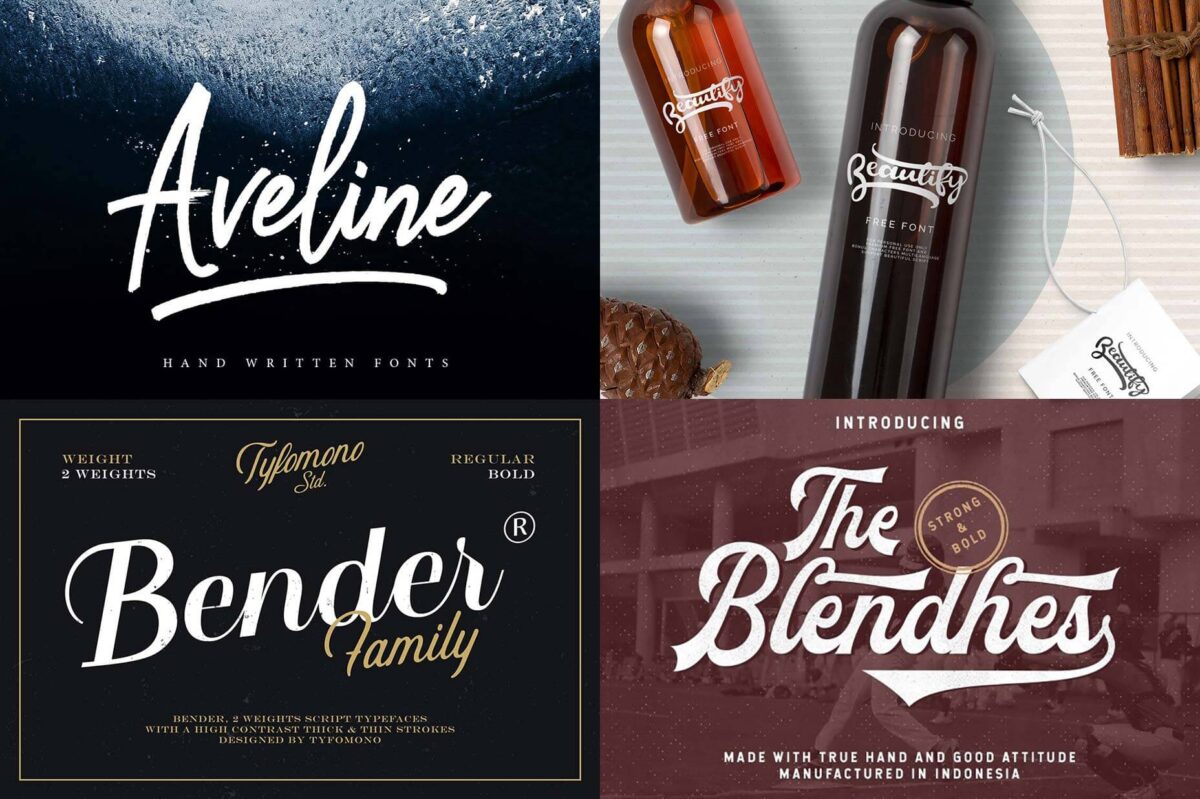
30 typographies commerciales à télécharger gratuitement
Nous avons toujours besoin de nouvelles typos. Ça tombe bien, webdesignerdepot et Mighty Deals proposent un pack de 30 typos à télécharger gratuitement.
Le pack de typo est très large et propose des choix très différents. Vous trouverez des typos très commerciales, des typos d’écriture à la main, d’autres au contraire font plus professionnelles. On sort clairement des typos habituelles du genre Helvertica et leur rigidité corporate. Certaines ne sont pas spécialement du meilleur goût, mais elles peuvent toujours se montrer utile pour certains projets et notamment pour du print. Pour télécharger les typos Alessandria, Andora, Anthasic, Aprillia, Aveline, Beautify, Bender, Blendhes, Blusty, Fibonaccy Journey, Fountain, Frutilla, Hadfield, Jelytta, Kitten, Lauren, Magnolia, Manyland, Matane, Milea, Monday Bay, Pink, Sansterdam, Santelia, Selima, Sophistica, Spirited, Sweet Buttermilk, Sydnee, et Valerissa gratuitement, il vous suffit de vous rendre sur ce lien, et de laisser votre email.